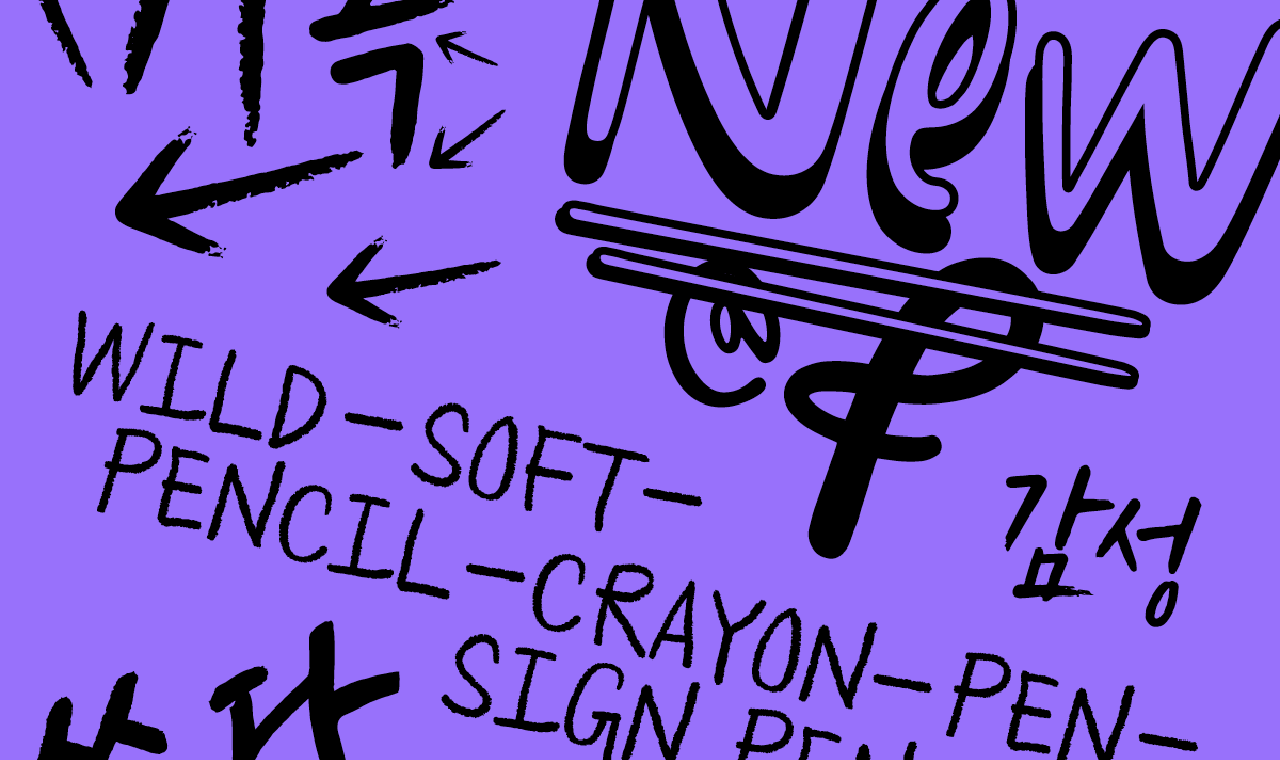
연필, 크레용, 페인트 마커 등, 도구의 질감과 감성이 살아 있는 윤디자인×공병각 캘리그래피 폰트 콜렉션
공병각의 손글씨는 글자가 정보뿐 아니라 감성까지 전달하는 매체라는 사실을 실감하게 합니다.
싸이월드로 소통하던 시절, 우리가 공병각의 손글씨에 울고 웃었던 이유이기도 하지요.
그리고 지금, 공병각은 여전히 인스타그램을 통해 사람들의 이야기를 듣고
우리의 일상을 관통하는 소소한 감정들을 손글씨에 담아내고 있습니다.
손글씨, 쓰는 사람의 마음이 듬뿍 담기는 매체
손글씨의 매력은 쓰는 사람의 감성과 진심을 고스란히 담아낸다는 점이에요.
이런 마음으로 써나가기 때문일까요?
‘머릿속에 행복한 글을 채워 넣기, 입으로 행복이 터져 나올 때까지’
‘좋은 사람은 언제나 진심인 사람이다’ ‘아 그럴 때는요, 바삭거리는 것을 먹으면 좀 나아져요’ 같은,
짧지만 힘이 있는 글귀들이 각자의 표정으로 어김없이 마음을 두드립니다.
패션, 광고, 출판 등 매체 환경은 매번 달라져왔지만, 글자로 감정을 나누고 싶다는 진심만은 언제나
일관되었기에 10년을 훌쩍 넘긴 지금까지 사람들과 글자로 교감할 수 있었습니다.
마음을 기록하는 다채로운 레시피, 공병각 콜렉션
이토록 손글씨에 진심인 작가, 공병각 아티스트 폰트 콜렉션은 Wild, Soft, 연필로 구성되어 있습니다.
질감이 살아 있는 캘리그래피 폰트 콜렉션을 기획하게 된 이유요?
우리가 소통한다는 것이 결국, 마음의 섬세한 결을 전하는 행위라고 생각했기 때문입니다.
우리가 소통한다는 것, 글씨를 쓴다는 것은 결국 진심을 전하는 일이기에, 마음의 떨림을 질감으로 표현한 손글씨 폰트를 제작하고 싶었습니다.
그러므로 소중한 마음을 그대로 옮겨 적고 싶은 날이 찾아온다면,
마음을 기록하는 다채로운 레시피, 공병각 아티스트 폰트 콜렉션의 힘을 빌려보는 게 어떨까요?
벅차오르는 감정을 가득 실어 키보드를 톡톡 두드리다 보면,
나도 몰랐던 내 마음의 결을 문득 발견하게 될지도 모르겠습니다.
야생의 숲, 솟구치는 파도, 황량한 사막
공병각 Wild
거칠고 자연스러운 것들만이 지닌 특유의 멋을 우리는 잘 알고 있습니다.
내 안에 꿈틀대는 생생한 이야기를 멋스럽게 표현하고 싶을 때,
날렵한 획과 거친 질감으로 카리스마를 발산하는 공병각 Wild와 함께하세요.
달콤한 마카롱, 딸기가 올라간 생크림 케이크, 무엇보다 손을 꼭 잡은 너와 나
공병각 Soft
달기만 한 이야기로 하루를 가득가득 채우고 싶을 때,
부드러운 조형으로 감성을 자극하는 공병각 Soft를 만나보세요.
연필로 꾹꾹, 마음을 꾹꾹
공병각 연필
연필은 처음과 가장 잘 어울리는 필기구입니다.
공병각 연필은 지우개로 박박 지울 수도 있지만, 결코 지우지 않는 각자의 소중한 이야기를 존중하는 폰트랍니다.
감추고 싶어 칠하면 칠할수록, 더욱 짙에 묻어나오는 진심
공병각 크레용
크레용은 미끄러운 필기감으로 거친 텍스처를 만들어내는 매력적인 도구입니다.
공병각 크레용은 수줍어 덧칠하면 칠할수록 진심이 묻어나와 들키고 마는, 귀엽고 사랑스러운 폰트랍니다.
오늘의 감성, 둥근촉으로 촉촉촉
공병각 둥근촉
페인트 마커 둥근촉은 흘러내릴 듯 촉촉한 감성을 지닌 도구입니다.
공병각 둥근촉으로 오늘치 감성을 한껏 발휘해보세요.
널 좋아해, 직진하는 감정의 속도
공병각 사각촉
페인트 마커 사각촉은 단번에 쓴 느낌을 자아내기 좋은 도구입니다.
감정에 직진이 필요한 날, 취기 대신 공병각 사각촉의 에너지를 빌려보면 어떨까요?